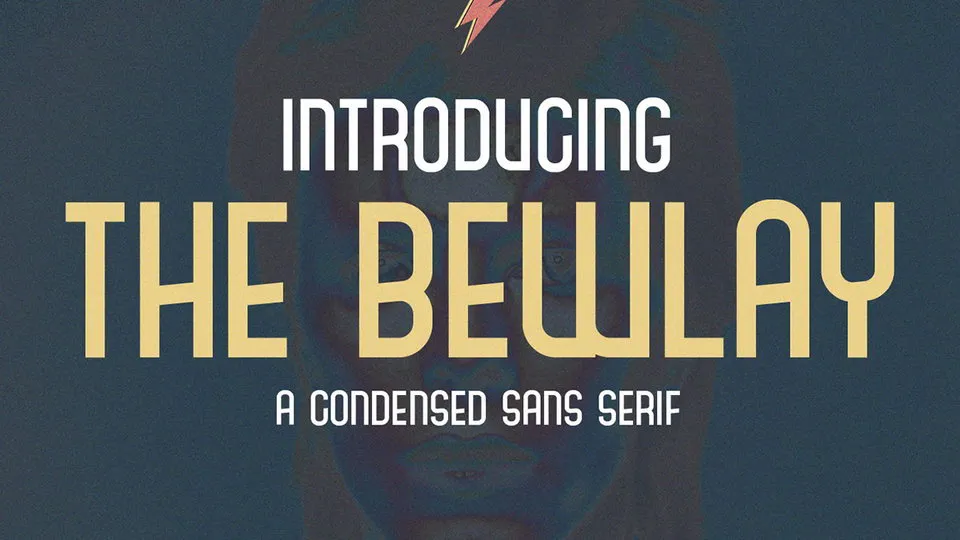
The Bewlay Typeface – Fonte Grátis
The Bewlay Typeface
Este é um tipo de feto sans serif ultra estreito com formas geométricas, perfeito para criar lemas criativos ou cartazes rapidamente. Ideal para camisetas, impressões, capas de livros ou revistas, postais de negócios, marcas de material de embalagem, avisos publicitários, letras digitais, posts no blog e até mesmo invitations de casamento. Além de sua utilidade em tais ambientes, The Bewlay Typeface é uma opção versátil para qualquer projeto que precise de um visual alegre e moderno. Para designers como vocês, Hamilton, a fonte é extremamente conveniente e inspiradora, o que a torna um recurso indispensável no seu arsenal gráfico.